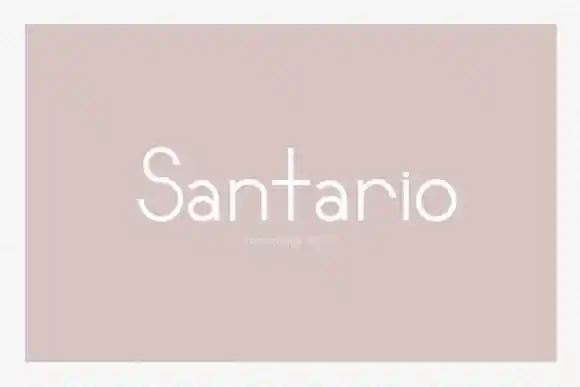
Santario Serif Font – Download Grátis
A Santario Serif Font é uma elegante tipografia serif que traz ao seu projeto um toque sofisticado, ao mesmo tempo clássico e moderno. Composta por linhas finas e robustas, esta fonte se destaca não apenas pela beleza visual mas também pela sua versatilidade. É perfeitamente adequada para uma variedade de projetos criativos, desde criações visuais como logomarcas, etiquetas de roupas ou cartões de visita, até artigos de papel, avisos e convites de casamento. Seja você um designer que busca um charme retrô em seus trabalhos, ou alguém que deseja dar um toque único aos materiais promocionais, a Santario Serif Font certamente fará seu trabalho. Não hesite em explorar suas possibilidades para fazer o seu design brilhar ainda mais.